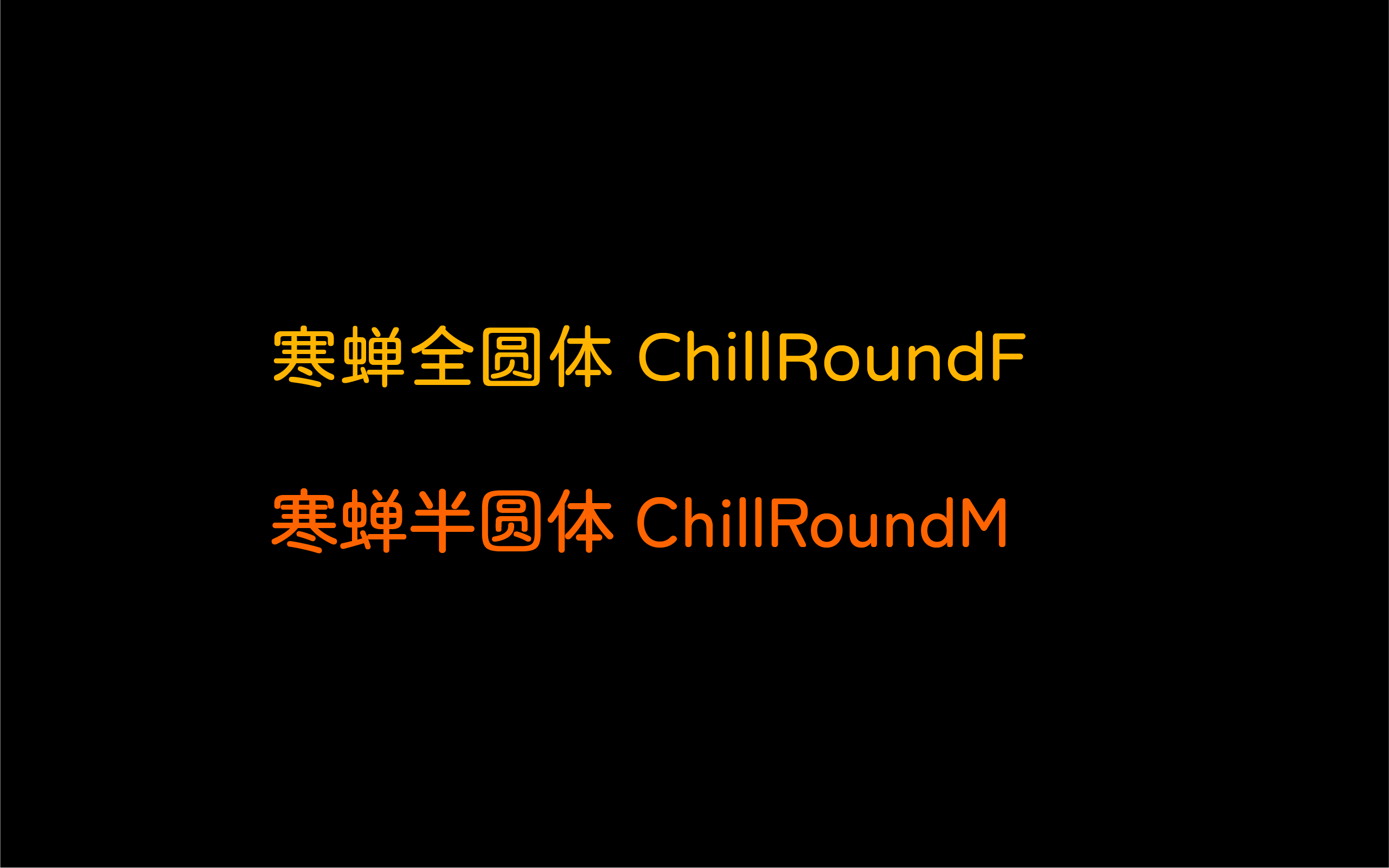
寒蝉全圆体3.200
寒蝉全圆体3.200,这款字体结构工整、笔画清晰,兼顾美观与易读性,适用于标题、正文、海报、包装、LOGO 等多种场景。字形优雅稳定,风格百搭耐看,适配日常排版与创意设计,让文字呈现更舒适、更具质感。寒蝉全圆体3.200一笔一画,皆是细节,以均衡的比例、流畅的线条打造舒适视觉体验,字形端正大气,风格简约现代。无论是商业设计、品牌宣传还是日常排版,都能轻松驾驭,让文字更有格调与力量。寒蝉全圆体3.200字体下载。
寒蝉全圆体 ChillRoundF
基于日本开源字型小杉圆体(Kosugi Maru)justfont粉圆 猫啃糖圆体 进行调整的圆体字型
更新为超大字符数量的字符集,使其应用范围更广。 综合考量各版本字形的使用并挑选合理的字形。 修正部分字形和补充部分字形。 调整到更均衡的排版。
全圆和半圆对比